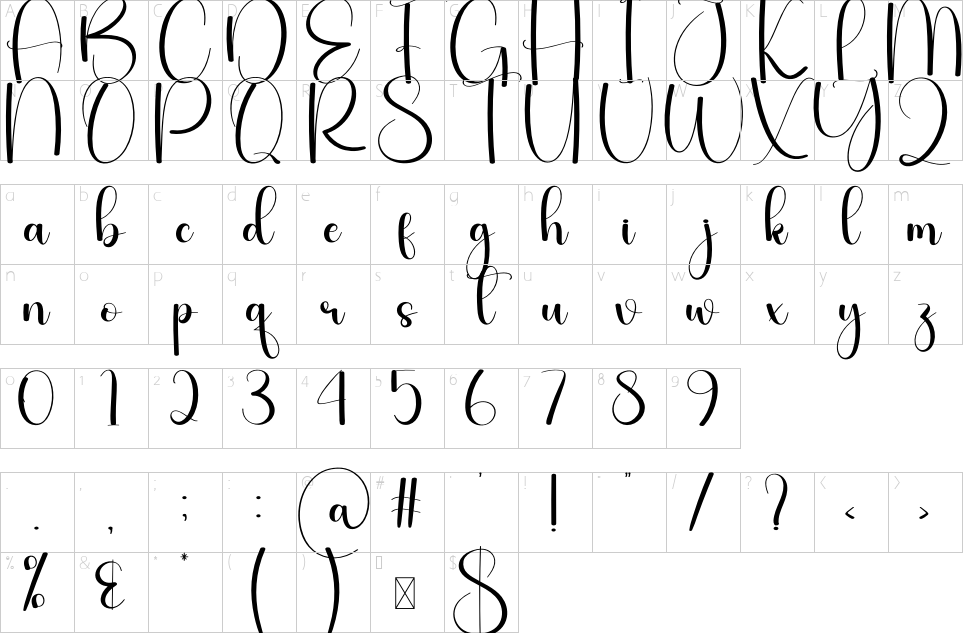
Aqui está uma descrição em português do Brasil para a página de download da fonte ‘Darling Font’, seguindo as regras fornecidas: A fonte Darling foi criada por um designer desconhecido, mas já conquistou muitos amantes da boa grife. Com um design minimalista e elegante, esta fonte oferece uma experiência visual fluida em seu layout, seja ele em aplicativos de leitura ou editoriais digitais. As pessoas que buscam algo versátil e limpo encontram nesta fonte a solução perfeita para seus projetos. Se você está procurando por uma fonte gratuita e de alta qualidade, o Darling é a escolha ideal. Disponível tanto para Windows quanto para Mac, esta opção lhe proporcionará gráficos profissionais em qualquer plataforma. Agradar seu público com a elegância e simplicidade do Darling é um passo garantido para criar uma impressão forte. Esta fonte tem sido baixada pelo número impressionante de 418 vezes, o que mostra sua popularidade entre os designers gráficos, tanto iniciantes quanto profissionais. Seja você um estilista digital ou criativo digitado, a Darling pode transformar seus projetos em algo ainda mais único e sofisticado. Não perca essa oportunidade de adicionar brilho ao seu trabalho com uma fonte tão versátil quanto ela é elegante.